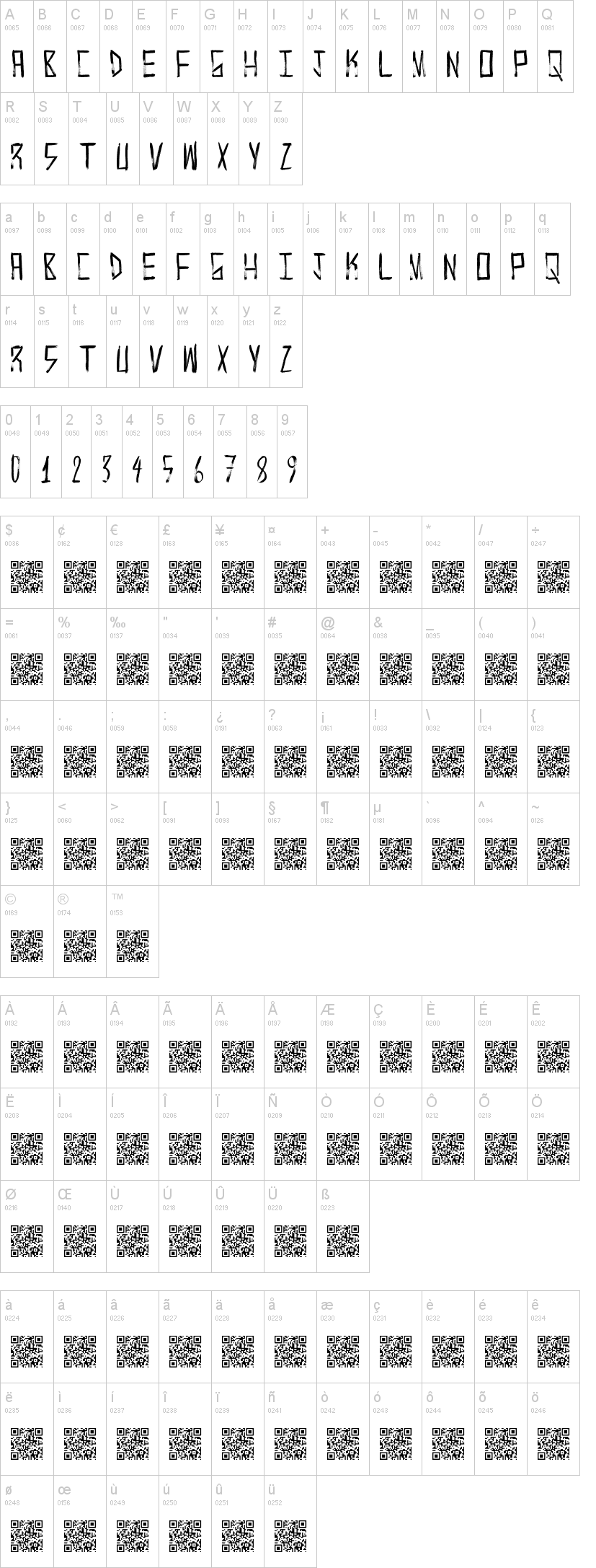
Kramps Handso是一款简约而细腻的手写字体,由荷兰设计师安德烈·克拉普斯(Andre Kramps)设计。该字体具有独特的手写风格,拥有自然的笔画,温暖的色调,以及清晰的笔画和细节。它的主要特点是字体的粗细变化,使字体更具表现力。Kramps Handso可用于各种类型的文本,包括广告,标题,书籍,日记,卡片等。它的字体设计优雅,美观,适用于各种文本类型,可以帮助您创造出独特的文字效果。内容介绍
Kramps Handso是一款非常不错的手写艺术字体,具有很好的视觉感,适合于文化类的宣传设计、商业类品牌的广告和产品包装设计以及个性化文字排版等较多场景。